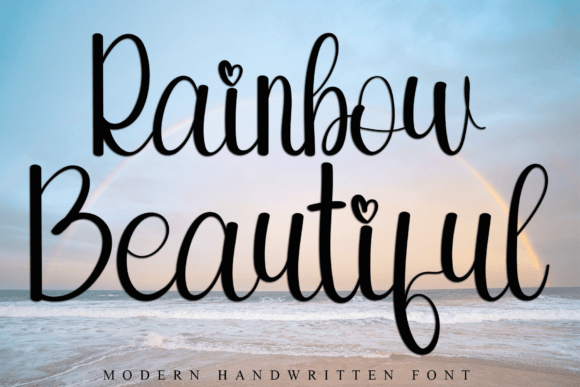
Rainbow Beautiful
Rainbow Beautiful : L'Affichant de Rêve pour un Design Visuellement Attrayant
** Si vous cherchez une police de caractères qui sait se mettre en valeur dans votre design, alors vous êtes au bon endroit ! **Rainbow Beautiful** est une police de caractères calligraphiée simple, joueuse et cool qui trouvera facilement sa place dans vos créations visuelles. **Les Atouts de Rainbow Beautiful**
• Simple et Joueur : avec sa belle calligraphie, **Rainbow Beautiful** est parfait pour les designers qui veulent apporter une touche de personnalité à leurs créations.
• Incréemment Versatile : cette police de caractères est idéale pour un large éventail de designs, du texte d'introduction à la publicité en ligne.
• Elevé au Niveau Supérieur : avec **Rainbow Beautiful**, vos idées créatives prennent vie et deviennent encore plus attrayantes.
**Intégrez Rainbow Beautiful dans Vos Projets** Si vous cherchez à donner un coup de pouce à vos créations visuelles, alors n'attendez plus ! Ajoutez **Rainbow Beautiful** à vos projets préférés et vous allez vite constater la différence. C'est la police de caractères idéale pour : * Les publicités en ligne * Les textes d'introduction * Les cartes de vœux * Les flyers * Et bien d'autres projets ! **Conclusion** Rainbow Beautiful est une police de caractères qui sait se mettre en valeur. Avec sa belle calligraphie, elle est idéale pour les designers qui veulent apporter une touche de personnalité à leurs créations. Intégrez-la à vos projets et vous allez vite constater la différence !